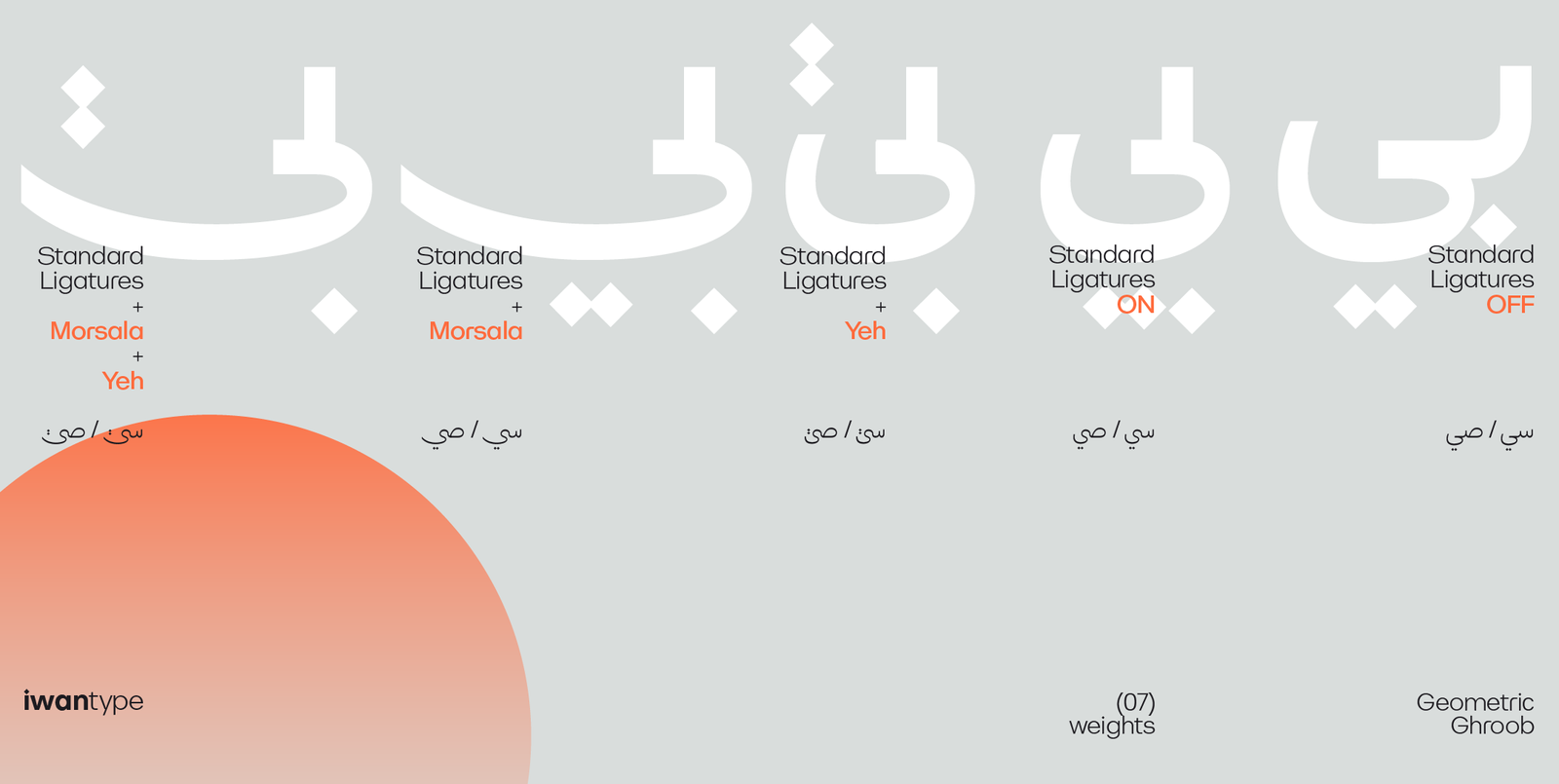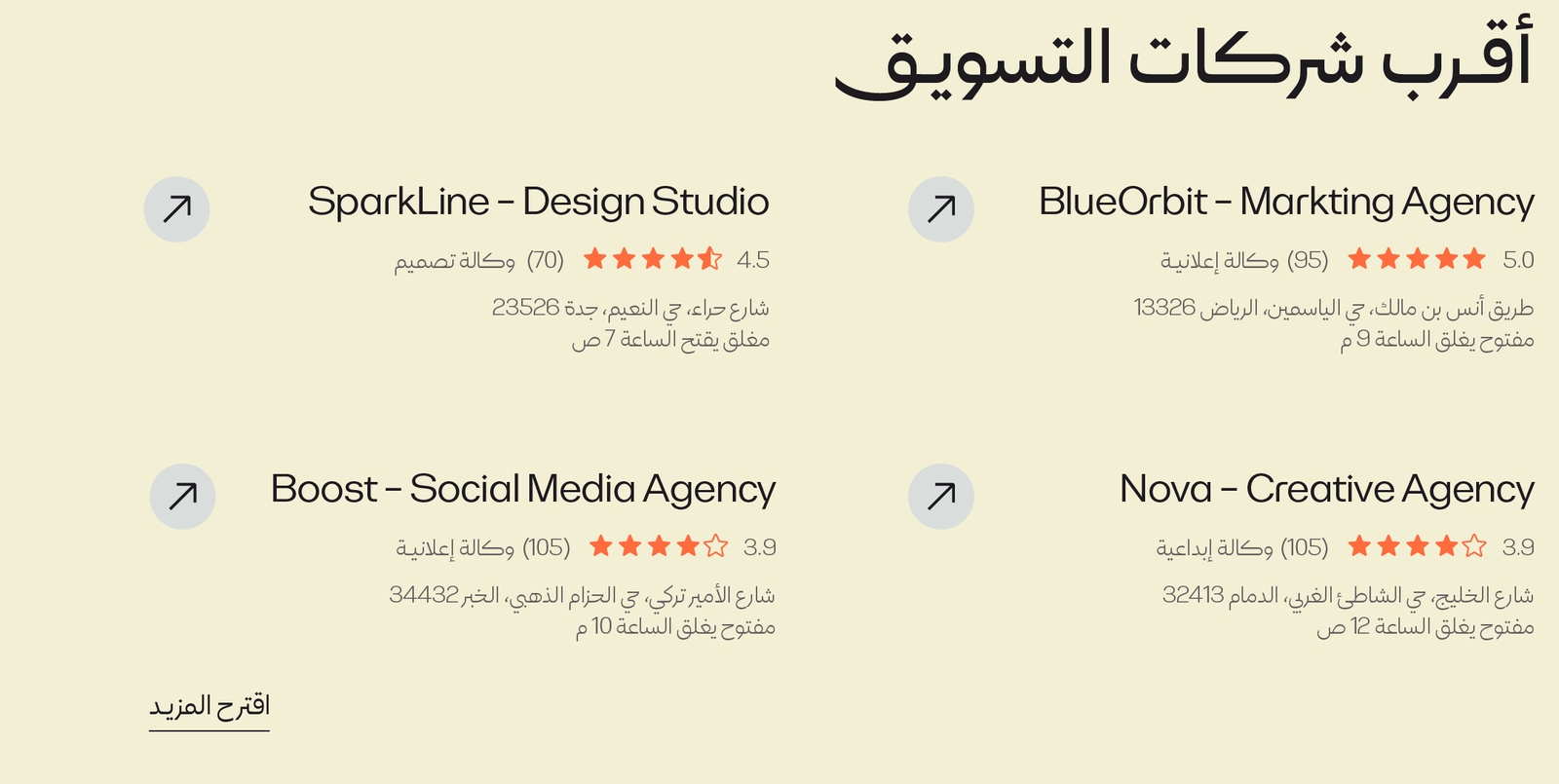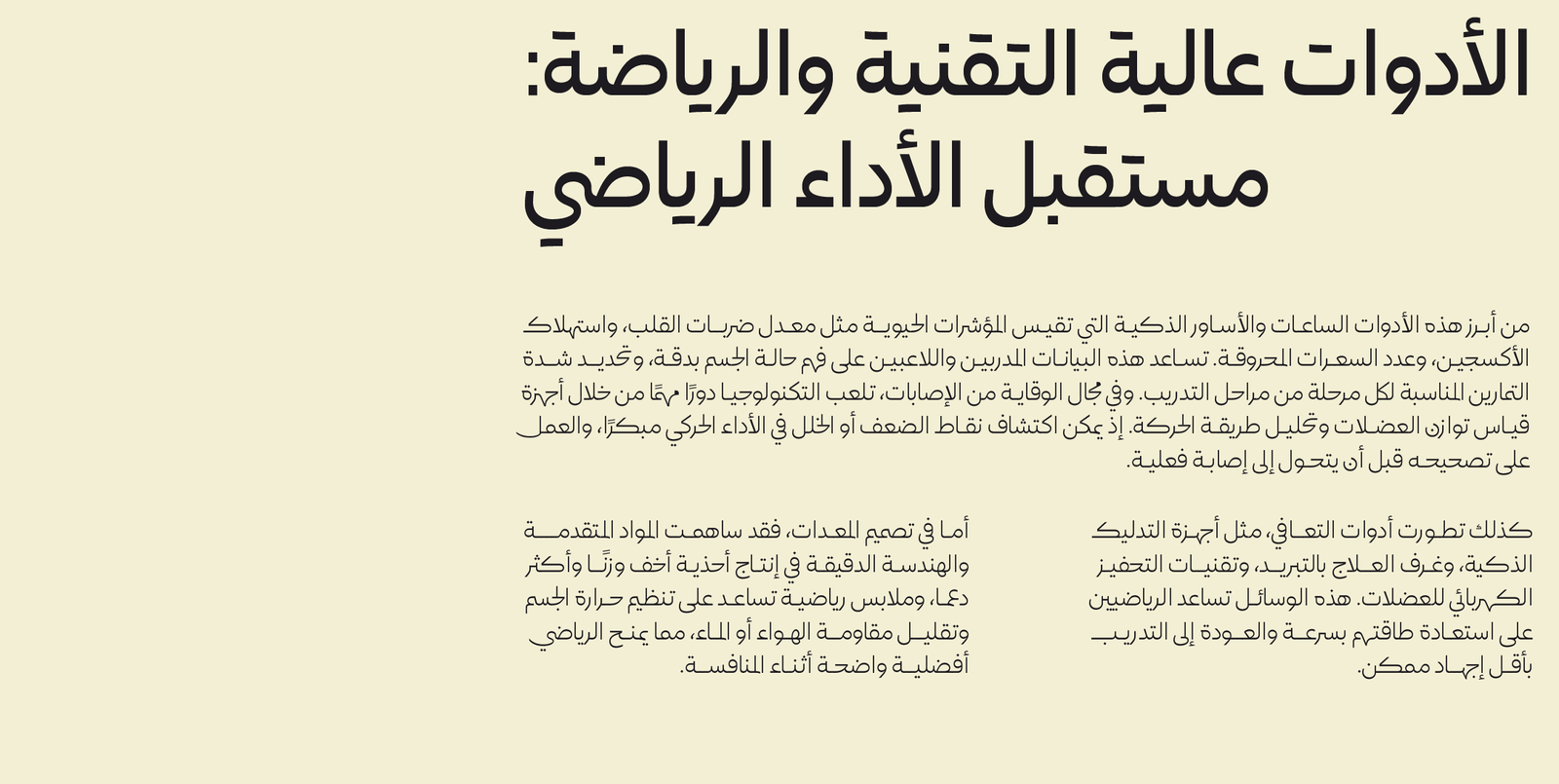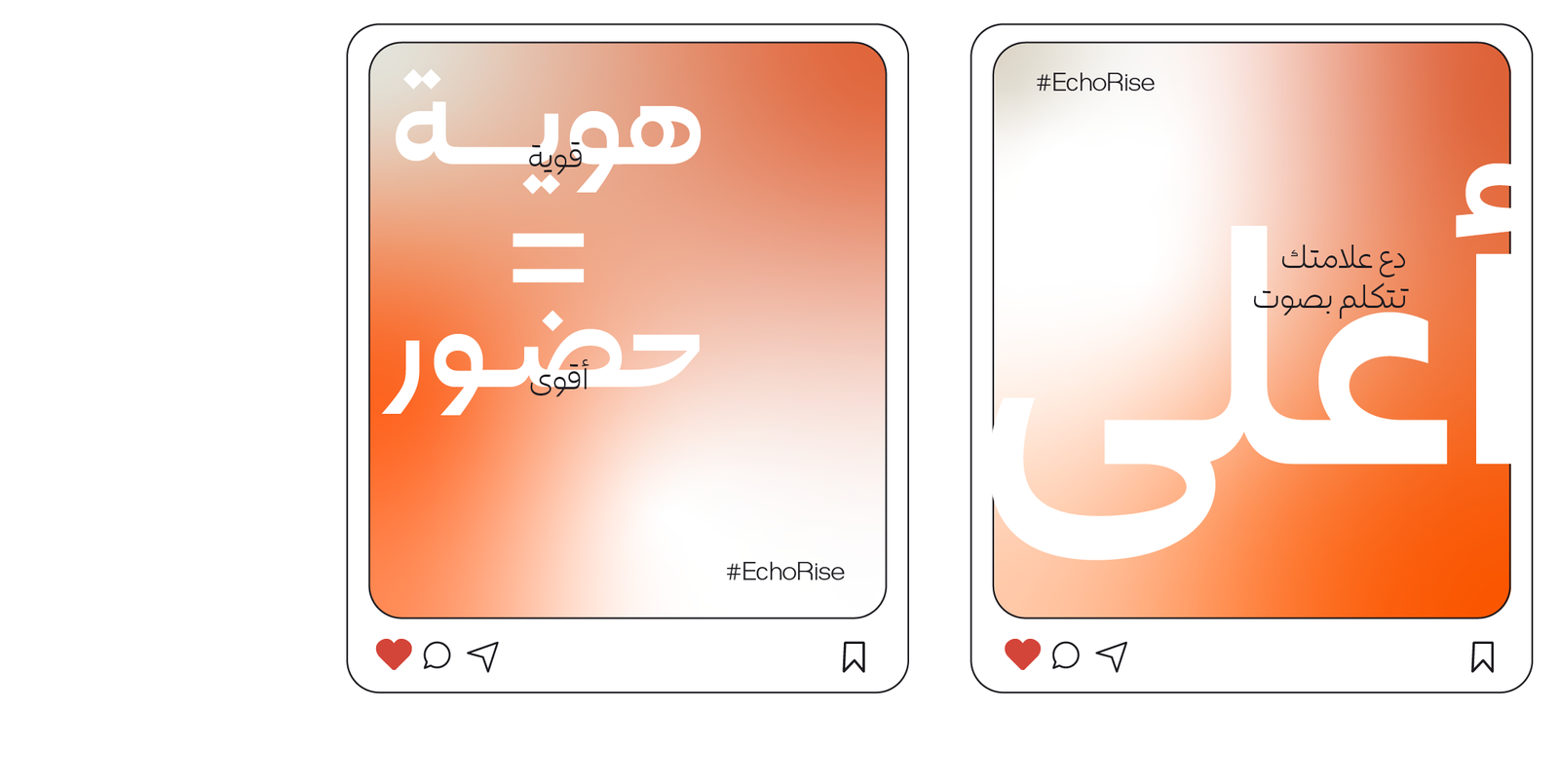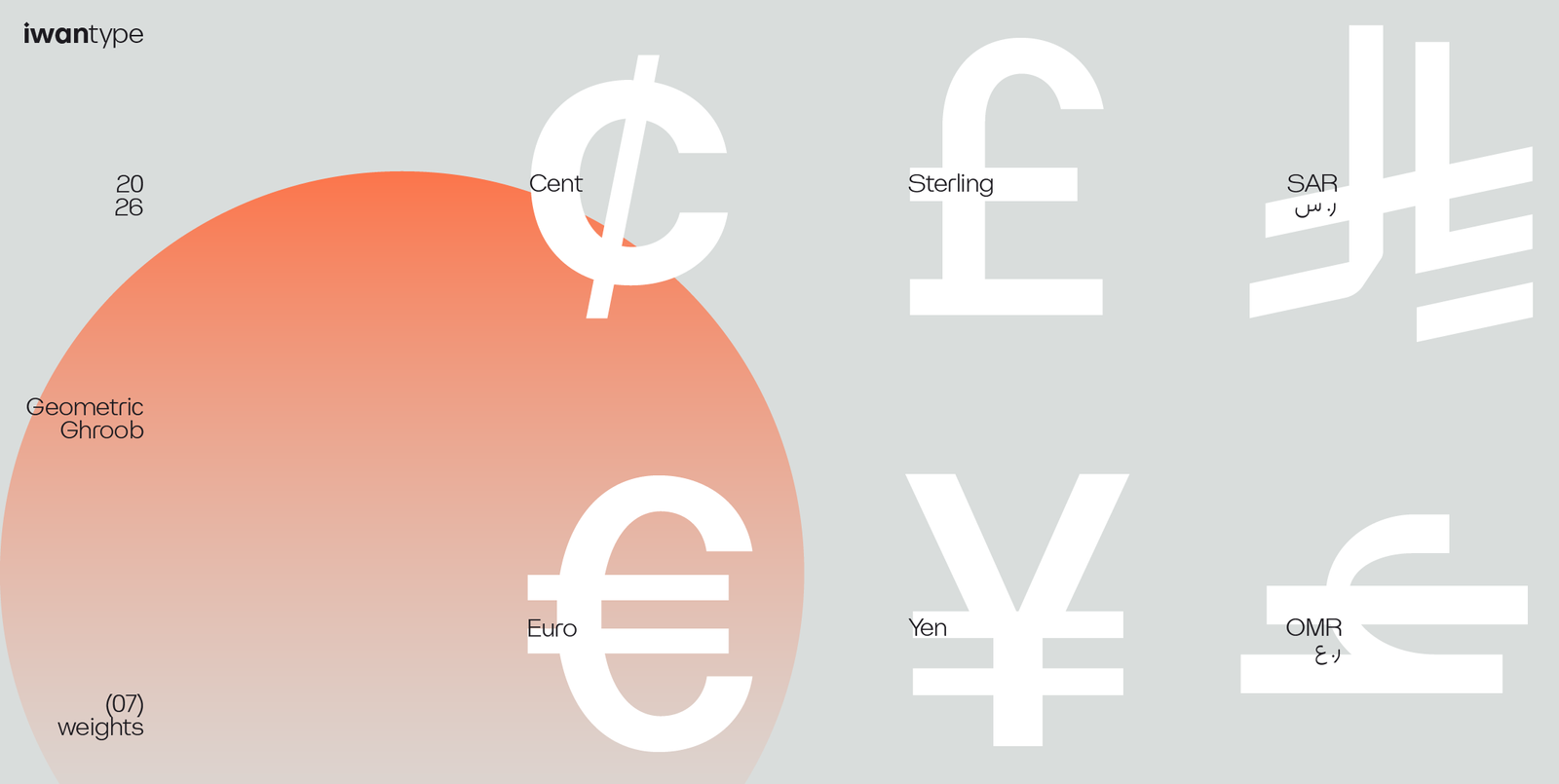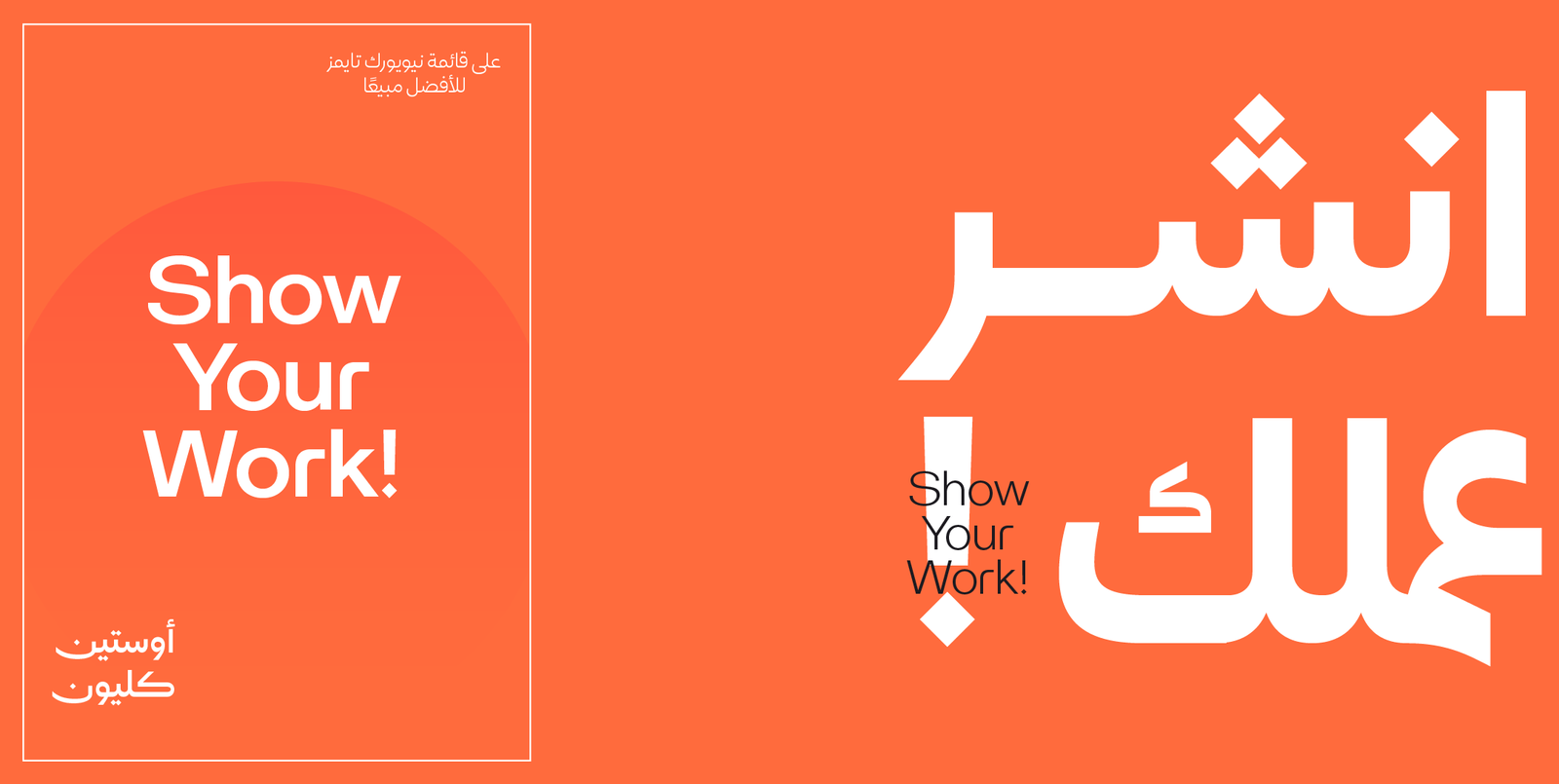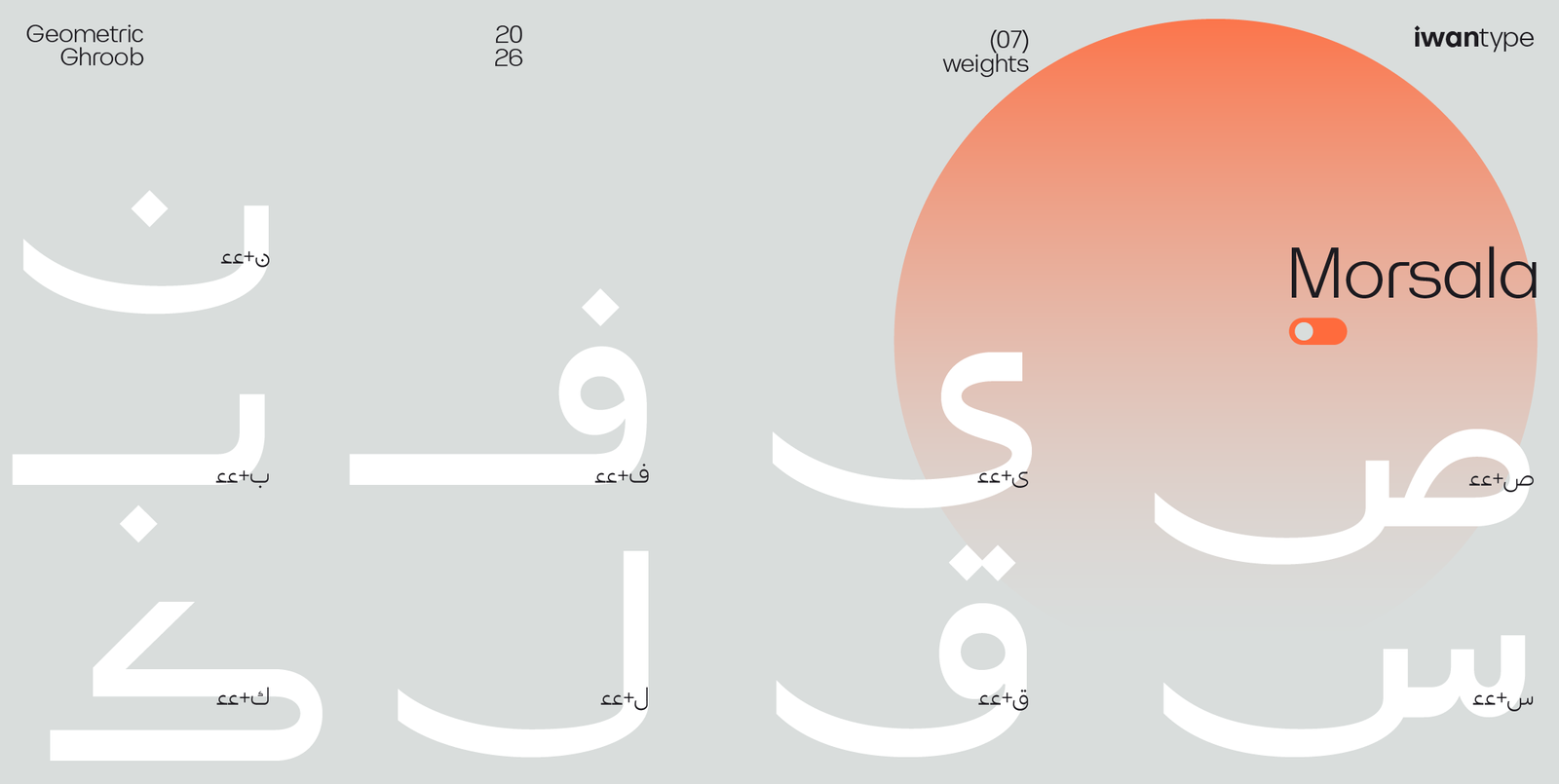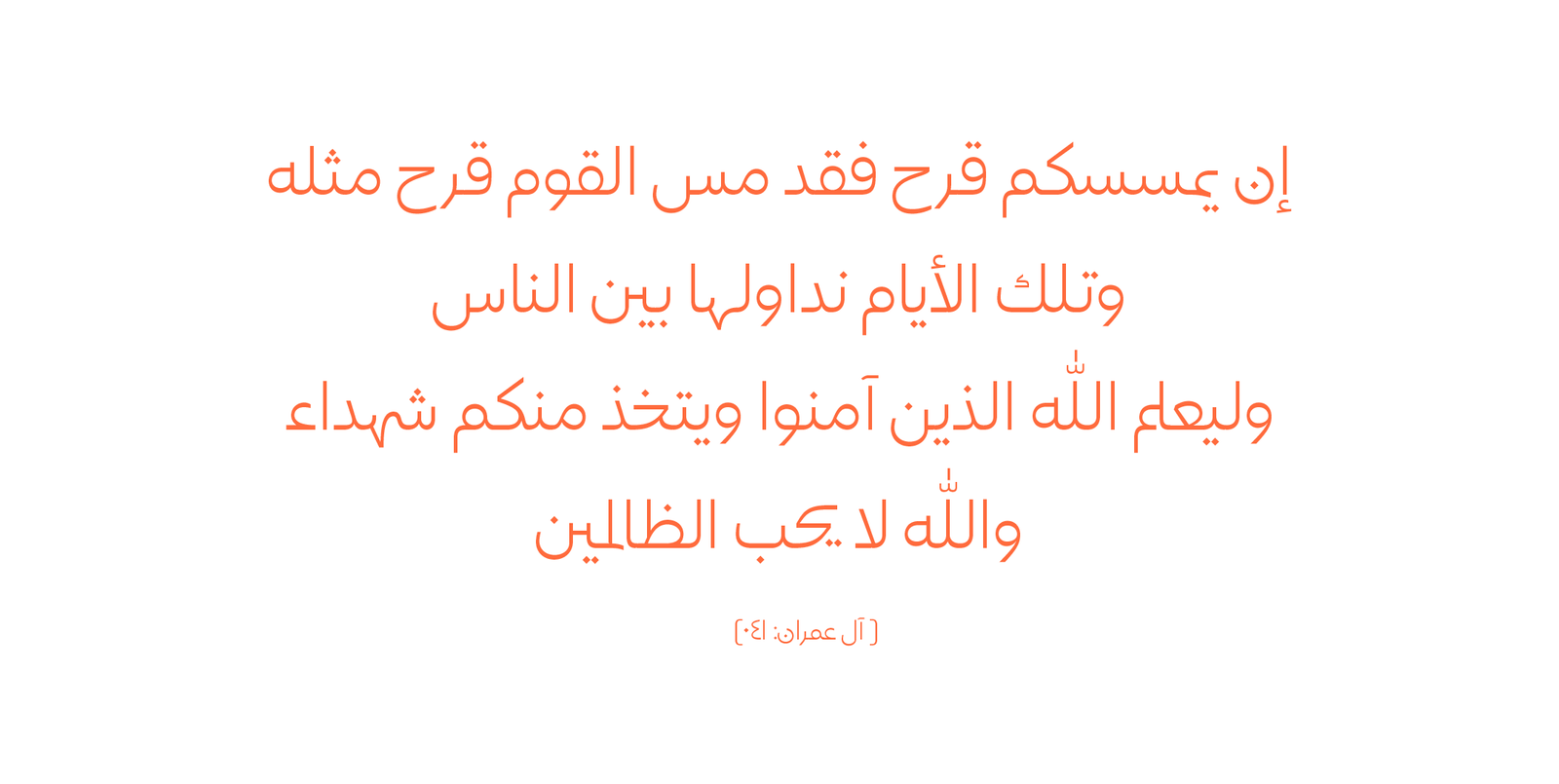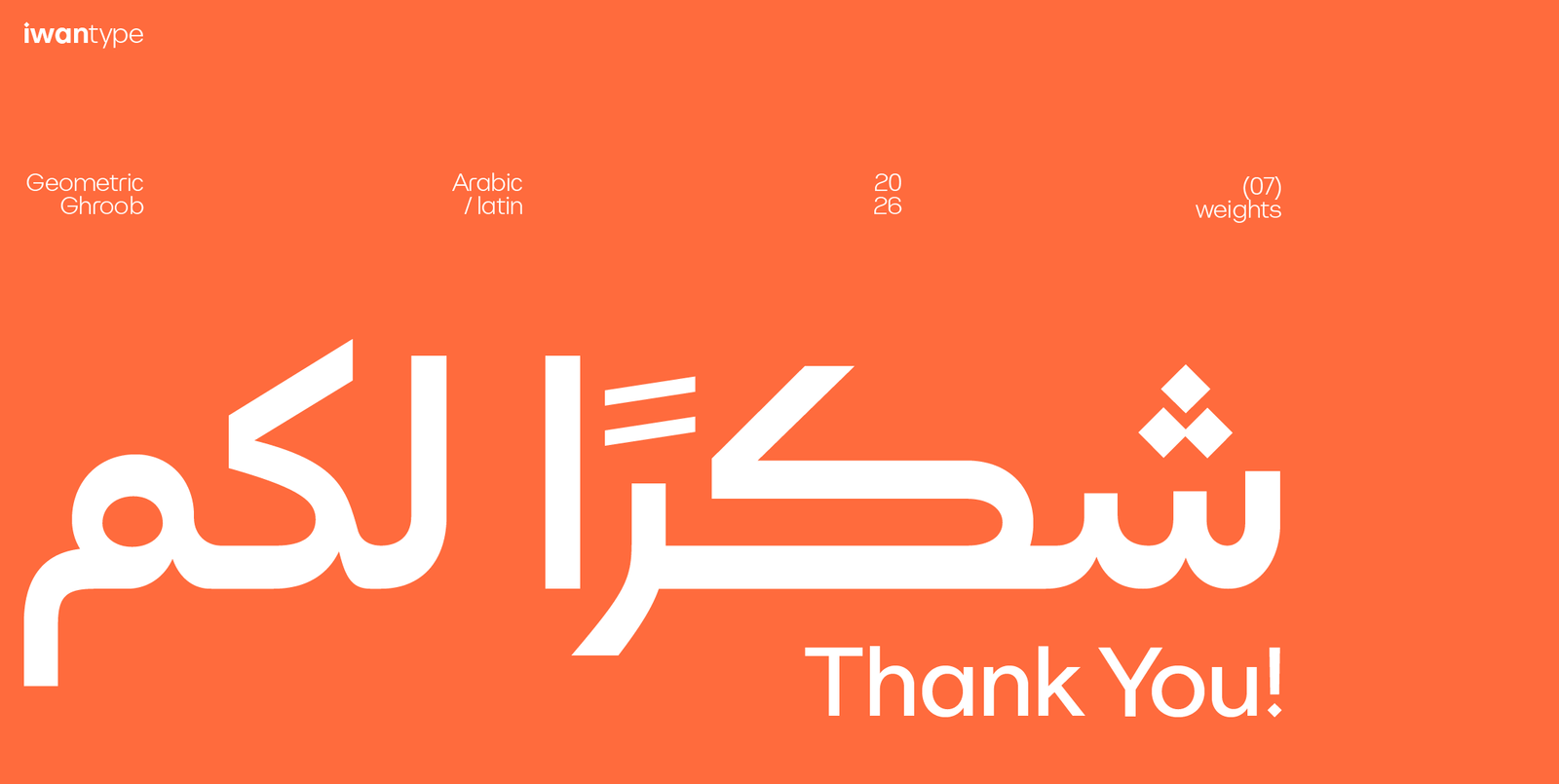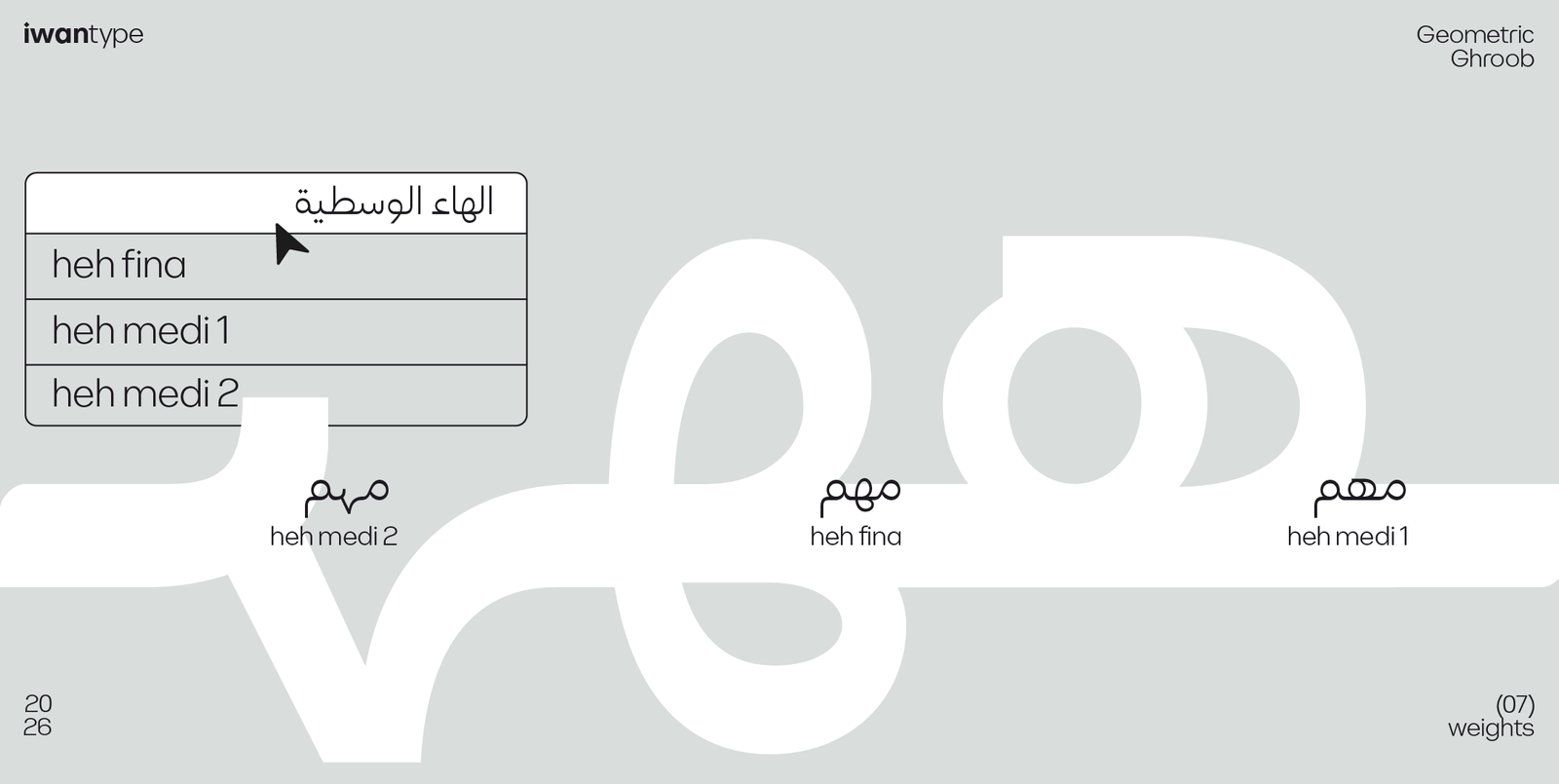
غروب هندسي – Ghroob Geometric – خط نسخ هندسي
غروب هندسي هو إصدار حديث من عائلة خط غروب، يعتمد على بناء هندسي واضح ومتوازن، مستلهم من الأشكال البسيطة والبنية النظامية للحروف العربية، ليقدّم تجربة بصرية معاصرة تناسب الاستخدامات الرقمية والطباعية.
تم تصميم الخط ليجمع بين الوضوح، التناسق، وسهولة القراءة، مع طابع هندسي يمنح النص حضورًا قويًا ونظيفًا، خاصة في العناوين والهويات البصرية.
يتميّز الخط ببنية مدروسة توازن بين الصرامة الهندسية وسلاسة الحرف العربي، مما يجعله مناسبًا لمجموعة واسعة من الاستخدامات مثل:
الهويات البصرية، واجهات التطبيقات، المواقع الإلكترونية، والإعلانات.
مميزات غروب هندسي:
يتضمن الخط العديد من مزايا OpenType التي تضفي عليه مرونة وتنوعًا في الاستخدام، مثل:
• أحرف مرسلة (تُفعَّل بإضافة “ءء” بعد الحرف)
• حرف ياء بنزول أقل: يقلل من نزول السطر ويعزّز انتظام النصوص.
• أحرف مركّبة تُحسّن سلاسة التراكيب وتناسق النص.
• سبعة أوزان كاملة تمنح مرونة واسعة في الاستخدام الطباعي.
• يدعم رمز الريال السعودي والريال العُماني ،ويتم تفعيلهما تلقائيًا عند كتابة الاختصارات: ر.س للريال السعودي ر.ع للريال العُماني
اللغات: العربية، اللاتينية، والكردية
الأوزان: ٧ أوزان